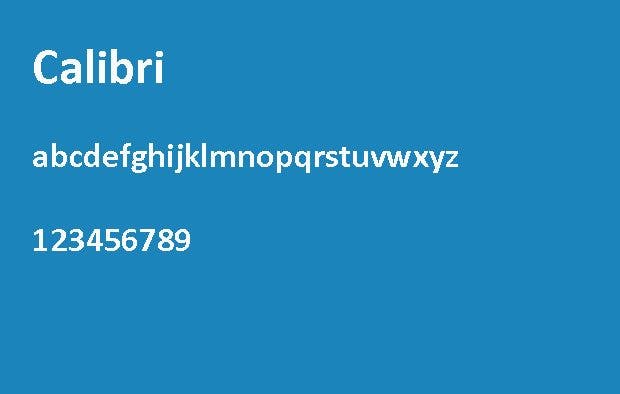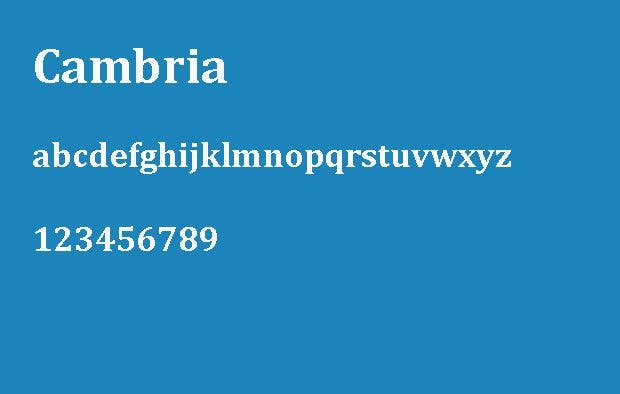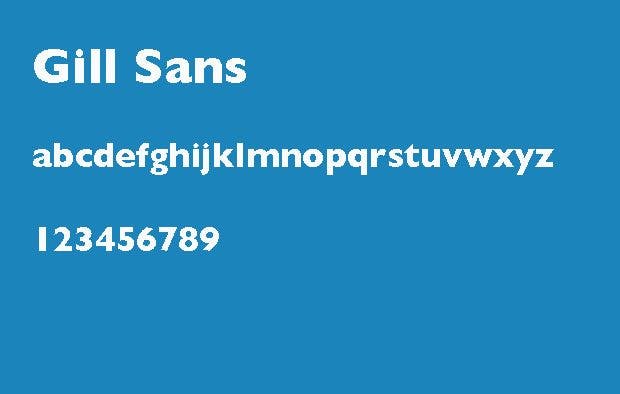
Bewerbung: Die 6 besten und schlechtesten Schriftarten
Wir wollen ja nicht oberflächlich sein, aber hin und wieder stimmt es: Der erste Eindruck zählt. Vor allem im Rahmen einer Bewerbungsmappe können ein merkwürdiges Layout, unschöne Rechtschreibfehler oder unwichtige Informationen dazu führen, dass die Unterlagen aussortiert werden – sofern Bewerber nicht durch superwichtige, extrem begehrte Fähigkeiten glänzen. Bei der Bewerbung können einige kleine und große Fehler passieren. Heute wollen wir uns mit der Schriftart beschäftigen und euch jeweils sechs Dos und Don’ts kuratieren.
Die besten Schriftarten für eine Bewerbung: Garamond, Helvetica, Georgia und Co.
Garamond: Die Schriftart dürfte nicht unbedingt jeder in seinem Alltag nutzen. Hier taucht sie auf, weil sie eine hervorragende Alternative zu Times New Roman ist. Times New Roman ist die beliebteste Schriftart – auch für Bewerbungsschreiben. Wer jedoch vermeiden will, dass die eigene Bewerbung sich optisch kaum von den anderen auf dem Tisch des Personalers unterscheidet, greift besser zu Garamond.
Helvetica gehört mit Sicherheit zum Adel der Schriftarten und hat es in unserem Alltag zu großen Ruhm gebracht. Verschiedene Unternehmenslogos wie etwa das von BMW kommen verdächtig nah an Helvetica Monospaced Bold heran. Und auch die New Yorker U-Bahn arbeitet mit der Schriftart im Rahmen der Beschilderung. Helvetica hat einen cleanen und zeitgenössischen Look, der dennoch professionell rüberkommt.
Georgia ist eine weitere Alternative zu Times New Roman. Diese Serifenschrift zeichnet sich durch Buchstabenformen mit dickeren Strichen aus, die es vereinfachen, auch kleinere Schriftgrößen lesen zu können. Zudem sieht sie auf Computerbildschirmen gut aus. Wer also digiale Bewerbungen in Form von Websites, Blogposts oder einfach nur PDF-Dokumente per Mail verschickt, liegt mit Georgia auf jeden Fall nicht verkehrt.
Cambria ist eine Serifenschrift, die ebenfalls auf Computer-Monitoren funktioniert. Als Teil der „Clear Type Font“-Sammlung aus Microsoft Office wurde sie sogar extra dafür entwickelt. Der Erfinder der Schriftart, Jelle Bosma, betont jedoch, dass sie unter der Prämisse, das neue Time New Roman zu werden, designt wurde – und somit auch für Papier geeignet ist. Die robuste Konstruktion und gute Lesbarkeit macht Cambria zu einer guten Wahl für Online- und Printprodukte.
Obwohl Calibri seit 2007 die Standard-Word-Schriftart ist, ist sie bei weitem nicht so populär wie Arial – das auf unserer Don’t-Liste zu finden ist. Calibri ist serifenlos und somit eine schöne Alternative zu Arial. Wer die Schriftart bei Schriftgröße 12 nutzt, kann bei einer optimalen Länge von 500 bis 750 Wörtern einen Lebenslauf verfassen, der über zwei Seiten geht – was optisch viel hermacht.
Gill Sans wurde im England der 1920er Jahre entwickelt. Sie gilt als einfache serifenlose Schrift, die leicht lesbar und vor allem in Großbritannien sehr populär ist. Die Schriftart findet sich auf MacOS und einigen Microsoft-Programmen. Berühmt wurde Gill Sans durch ihren Einsatz im „Keep Calm and Carry On“-Poster, das eine britische Buchhandlung wiederentdeckt und verbreitet hat.